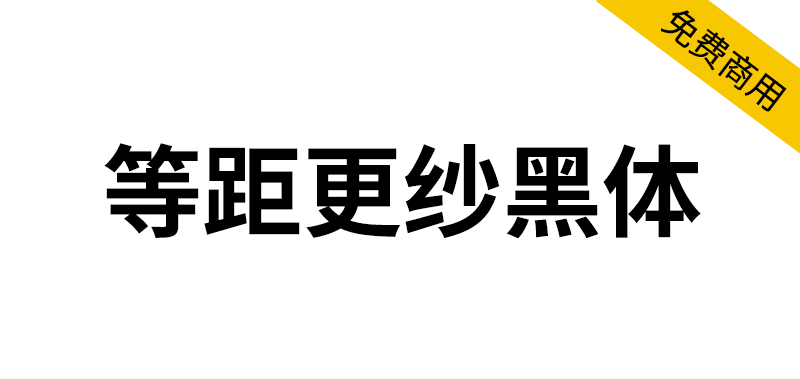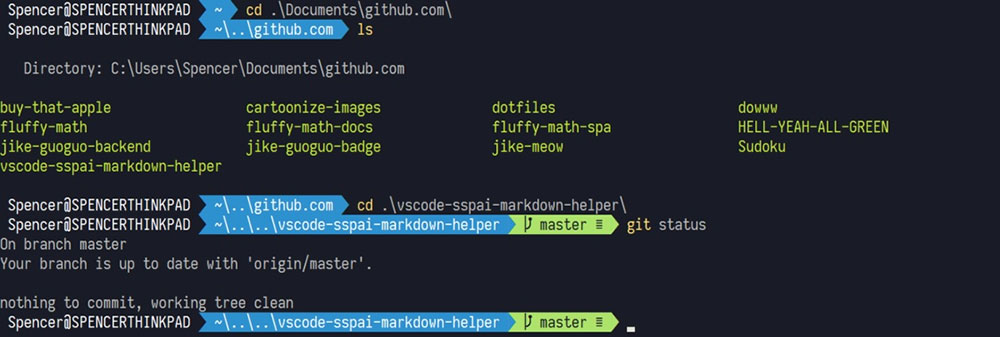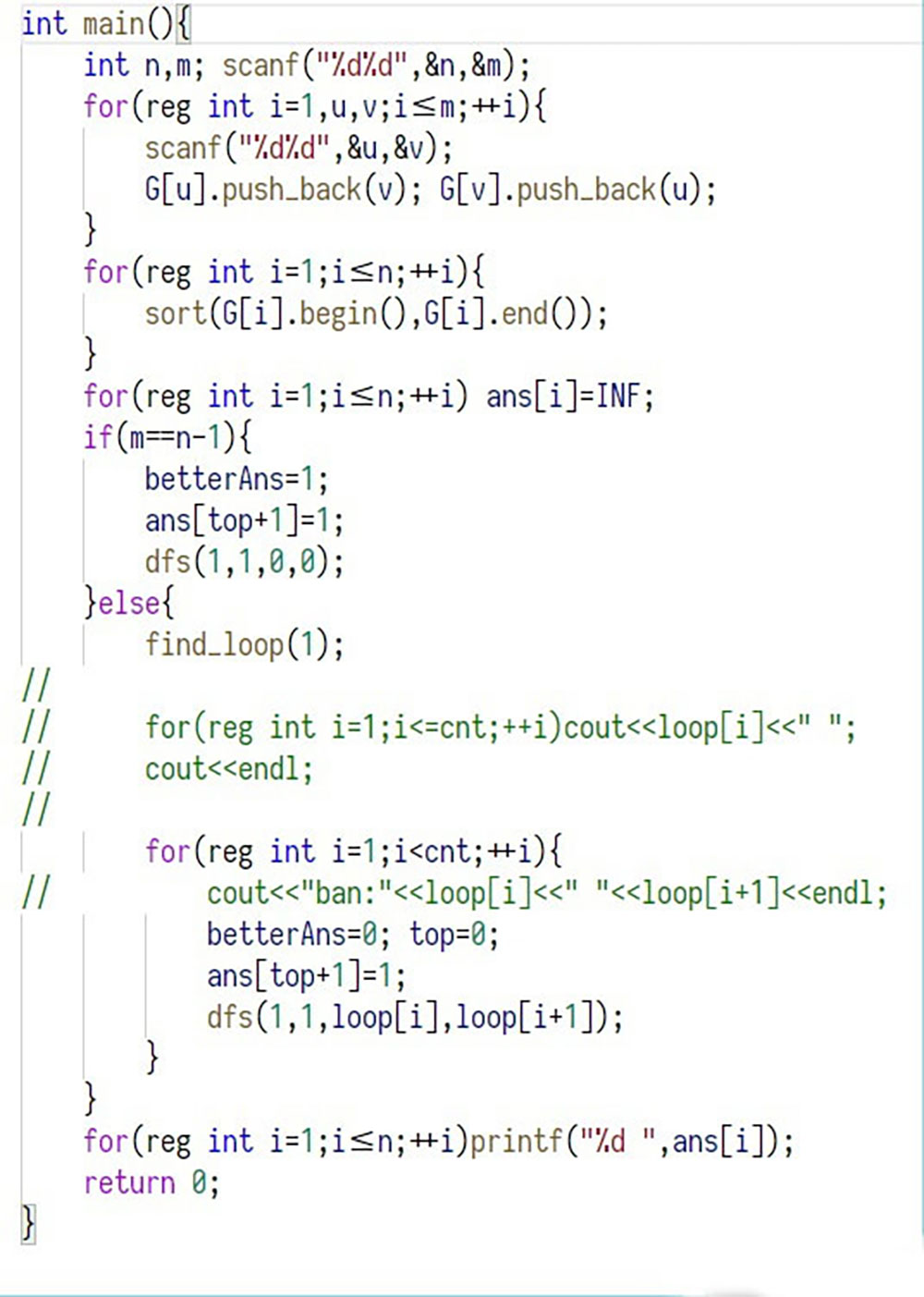
等距更纱黑体(Sarasa Mono)是一款专为编程和文字排版设计的开源等宽字体,属于更纱黑体系列的分支,等距更纱黑体基于开源字体 Iosevka和思源黑体优化而来,尤其适合代码、编程、终端显示,兼具美观性、可读性和功能性,已成为众多开发者、设计师的热门选择。
○ 等宽设计:每个字符(包括中文、英文、符号)宽度相同,确保代码对齐整齐,适合编程、终端、表格等场景。
○中西文协调:中文字形采用思源黑体的优雅风格,英文部分参考 Iosevka,保持简洁易读。
○优化符号显示:对编程常用符号(如{}[]|<>)进行特殊处理,增强辨识度,减少视觉混淆。
○多字重支持:提供从 Light 到 Bold 多种字重(粗细),适应不同场景需求。
○完整字符覆盖:支持汉字、假名、拉丁字母、符号等,覆盖 Unicode 常用范围。
等距更纱黑体凭借其对多语言混排和编程场景的深度优化,如果你需要一款既能优雅显示中文,又能完美处理代码的字体,等距更纱黑体是极佳的选择。